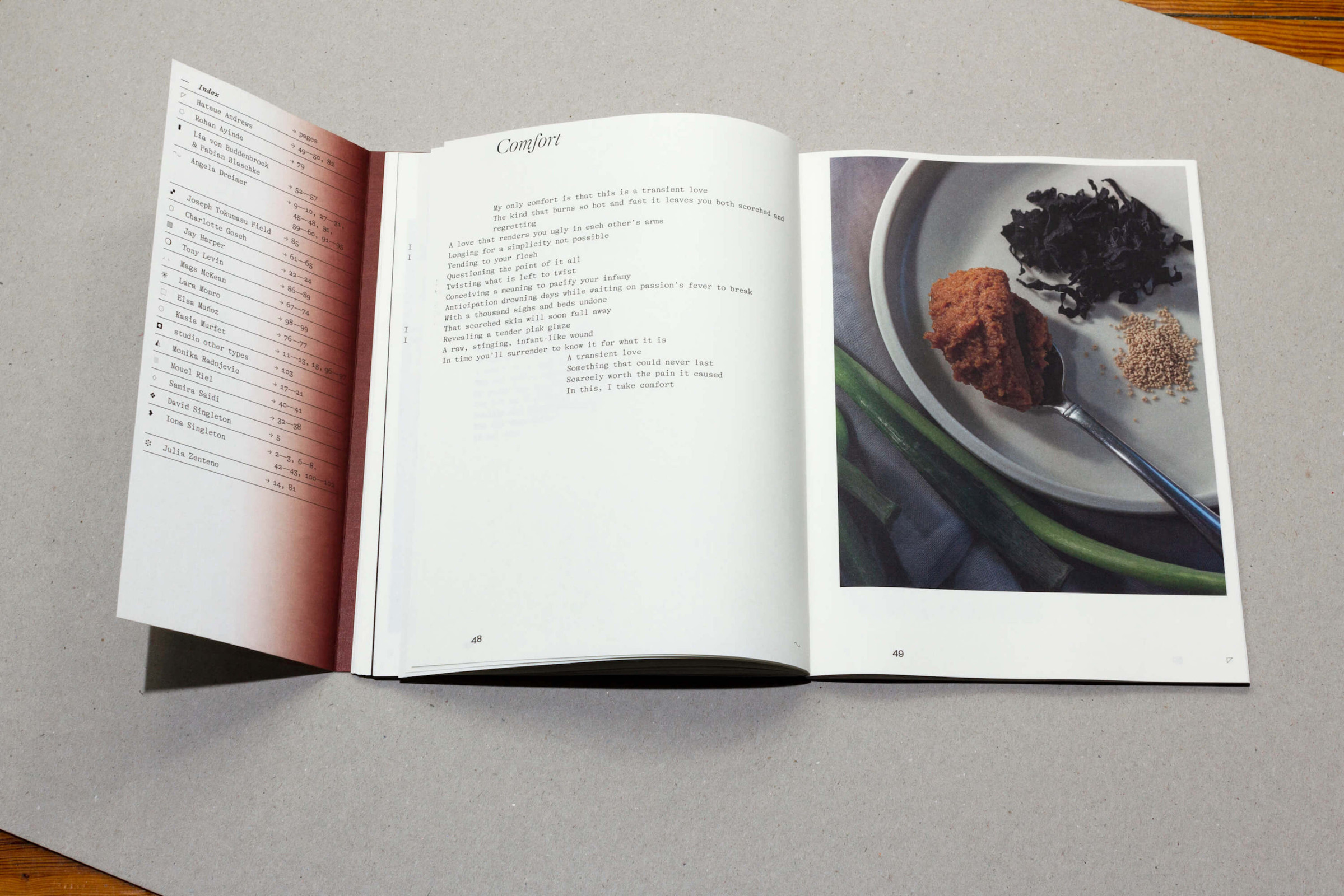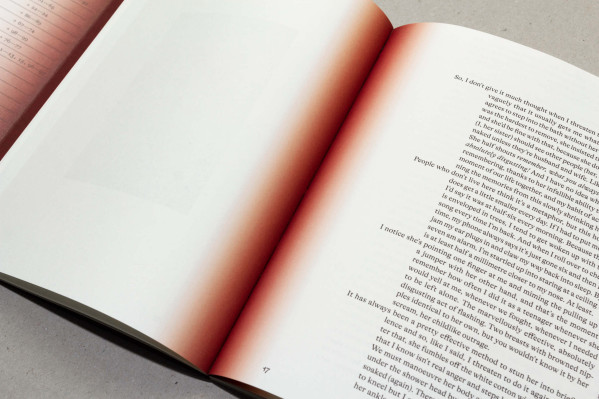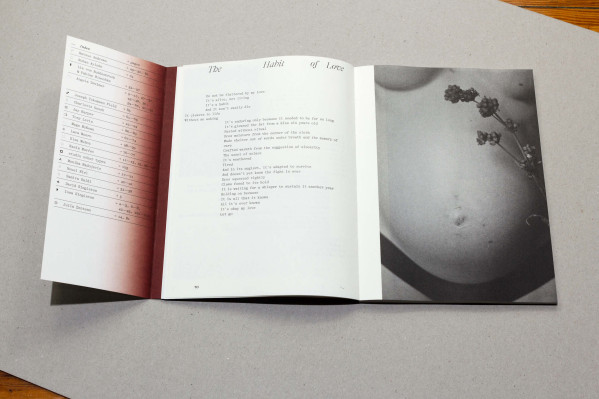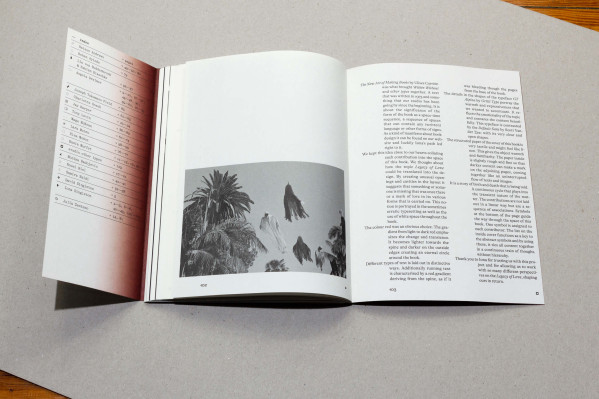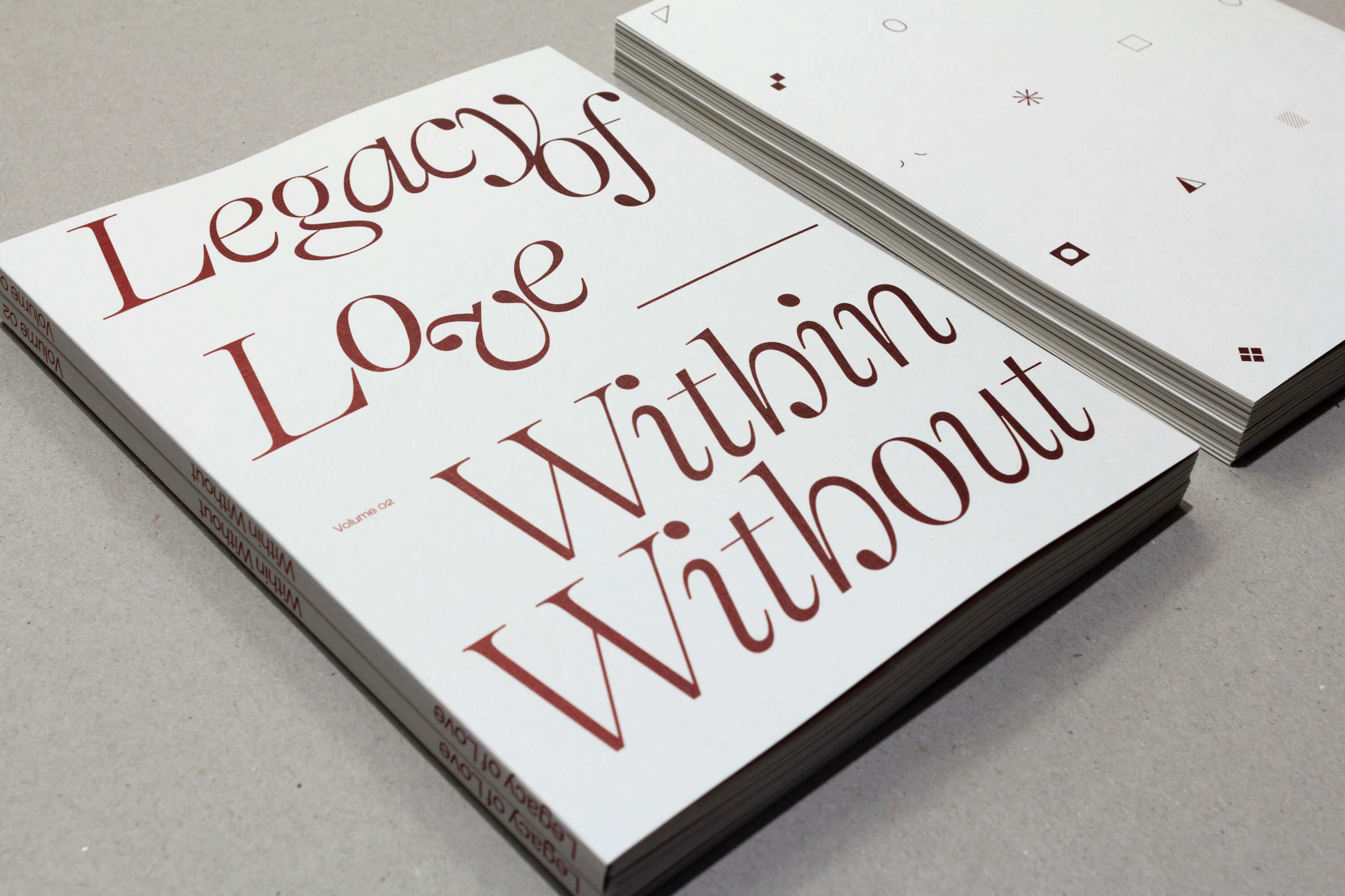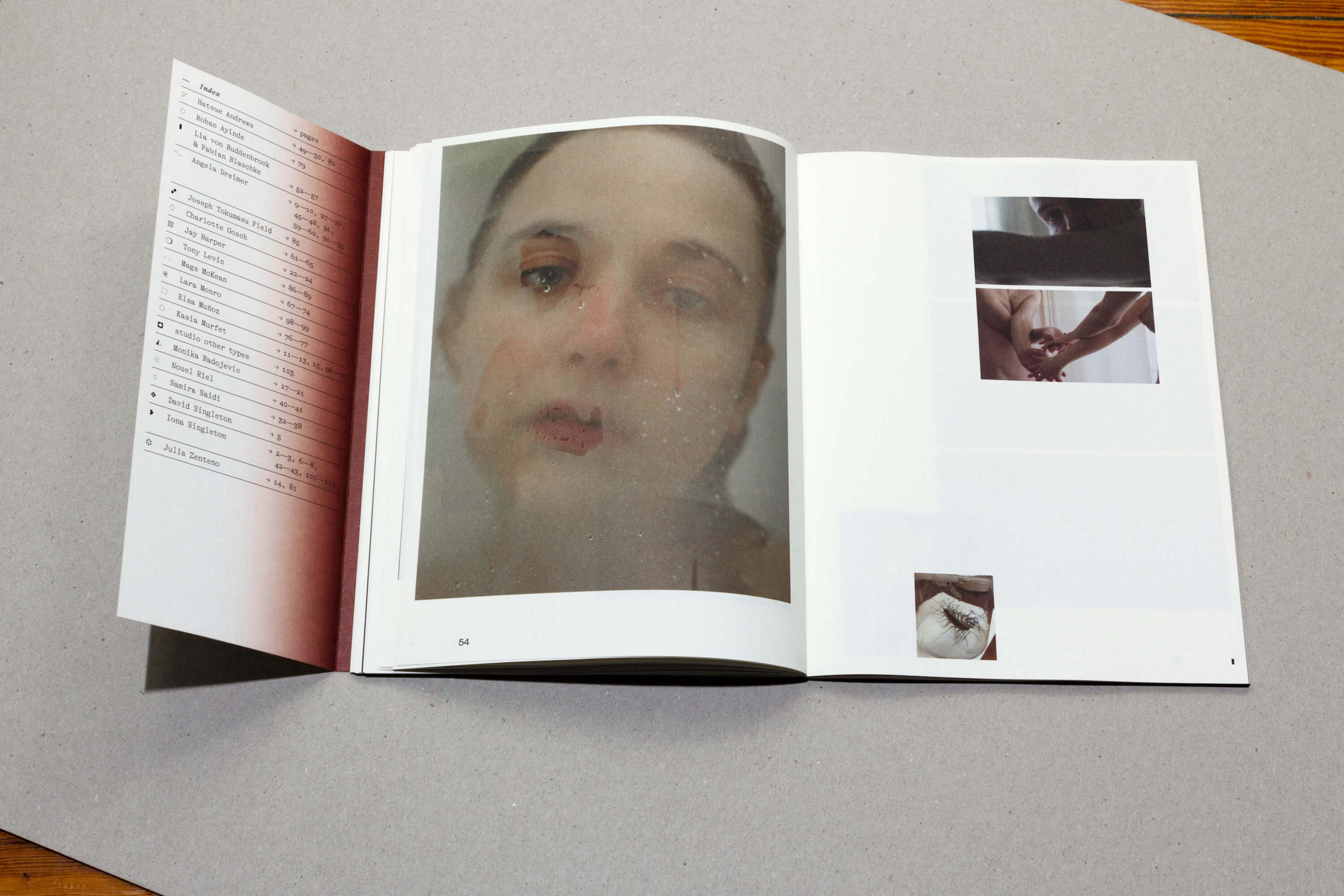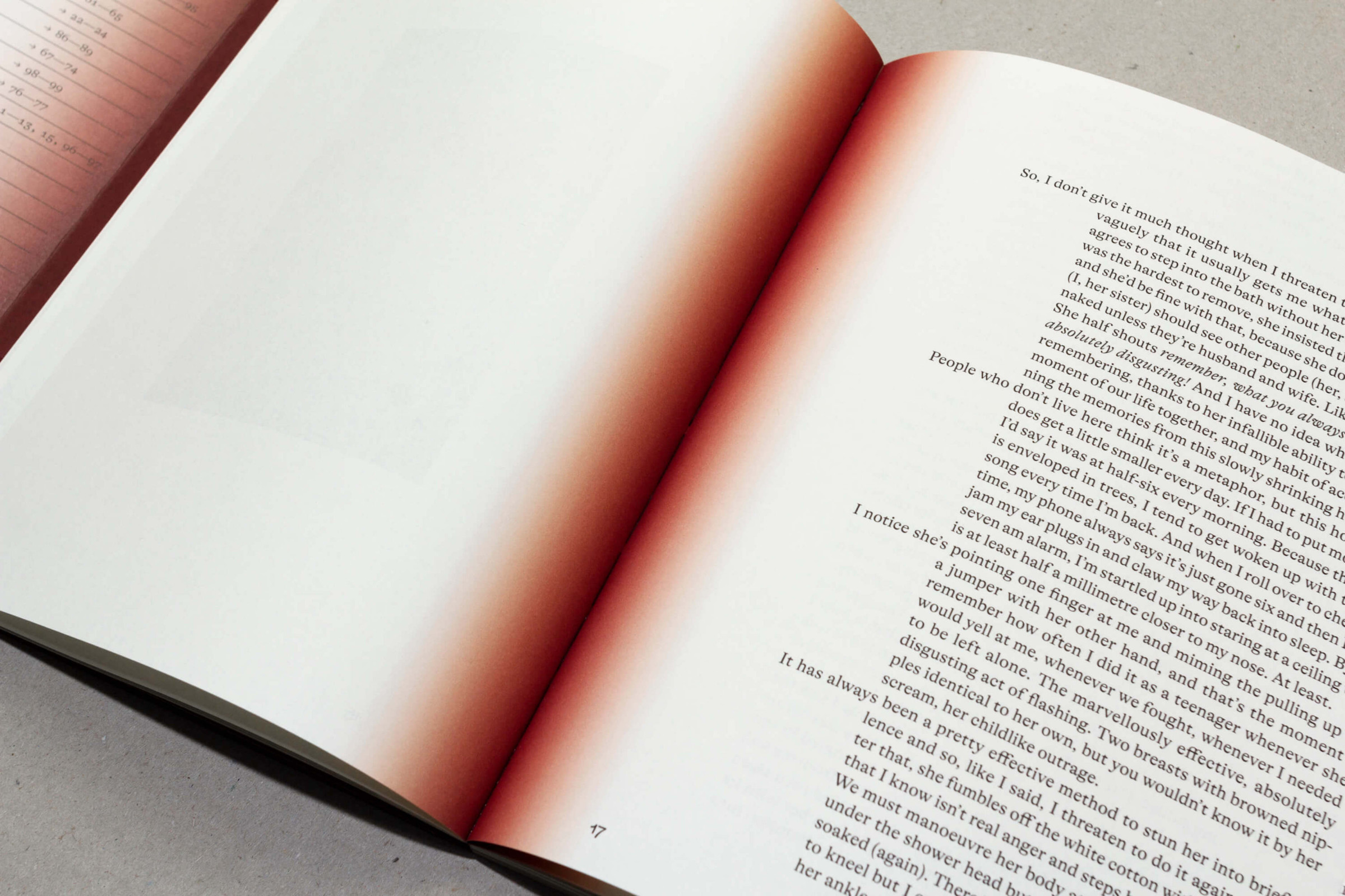
Within Without Vol. 02 – Legacy of Love
Buch
The New Art of Making Books von Ulises Carrión hat Within Without und studio other types zusammen­gebracht. Ein Text, der 1975 geschrieben wurde und an der uns von Anfang an sehr am Herzen lag. Es geht um die Bedeutung der Form des Buches als Raum-Zeit-Sequenz, eine Abfolge von Räumen, die jede (Schrift-)Sprache oder andere Formen von Zeichen enthalten können. Als eine Art Manifest über Buchgestaltung ist es auf unserer Website zu finden, und glücklicherweise führte Ionas (Within Without) Weg direkt dorthin.
Wir haben uns diese Idee zu Herzen genommen und jeden Beitrag im Raum dieses Buches eingebracht. Wir überlegten, wie das Thema Legacy of Love in der Gestaltung umgesetzt werden kann: Durch die Schaffung von ungewöhnlichen Öffnungen und Hohlräumen im Layout wird suggeriert, dass etwas oder jemand fehlt, das oder der/die einmal vorhanden war, oder ein Zeichen der Liebe in ihren ver­schiedenen Formen, das weiter getragen wird. Diese Idee wird durch versetzte Absätze und die Ver­wendung von Weißraum zum Ausdruck gebracht.
Die Farbe Rot war eine naheliegende Wahl. Der Farbverlauf von hellem zu dunklem Rot unterstreicht den Wandel und die Vergänglichkeit. Es wird zum Buchrücken hin heller und an den Außenkanten dunkler, wodurch ein ewiger Kreis um das Buch herum entsteht.
Die verschiedenen Textarten sind auf unterschied­liche Weise angeordnet. Zusätzlich ist der Fließtext durch einen roten Farbverlauf gekennzeichnet, der vom Buchrücken ausgeht, als ob er vom Buchboden aus durch die Seiten blutet.
Die Details in den Formen der Schrift GT Alpina von Grilli Type zeigen Wärme und Ausdruckskraft. Sie spiegeln die Emotionalität des Themas wider und umgarnen den Inhalt. Im Kontrast dazu steht die Default Sans von Scott Vander Zee mit ihren sehr klaren und offenen Formen.
Das strukturierte Papier des Einbandes ist haptisch und fühlt sich wie Leinen an. Das verleiht dem Objekt Wärme und Vertrautheit. Das Papier im Innern ist rau und dünn, sodass sich dunklere Inhalte auf den darunter liegenden Seiten abzeichnen können und sich alles wie ein ununterbrochener Fluss von Texten und Bildern zusammenfügt.
Es ist eine Geschichte von der Geburt und vom Tod. Ein ständiger Kreislauf, der mit dem Ephemeren des Themas spielt. Die Beiträge sind nicht linear ange­ordnet, sondern stellen eine Abfolge von Assozi­ationen dar. Symbole am unteren Rand der Seite weisen den Weg durch den Raum dieses Buches. Allen Beitragenden ist ein Symbol zuge­ordnet. Die Liste auf der Innenseite des Umschlags dient als Schlüssel zu den abstrakten Symbolen und verbindet damit alle Inhalte zu einem kontinuierlichen Ge­dankengang ohne Hierarchie.
Typefaces: GT Alpina von Grilli Type
& Default Sans von Scott Vander Zee